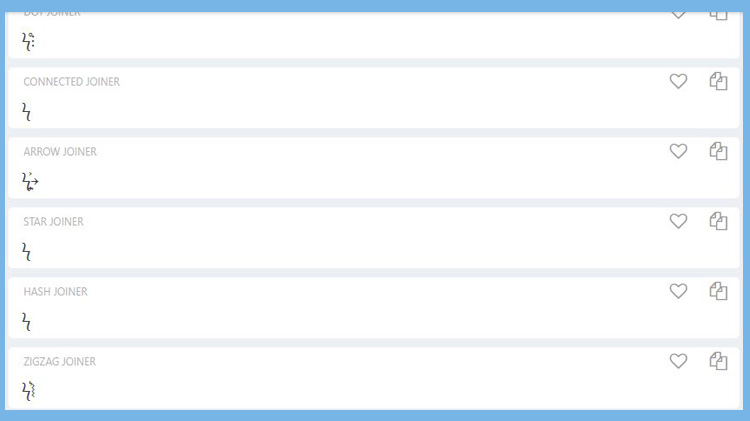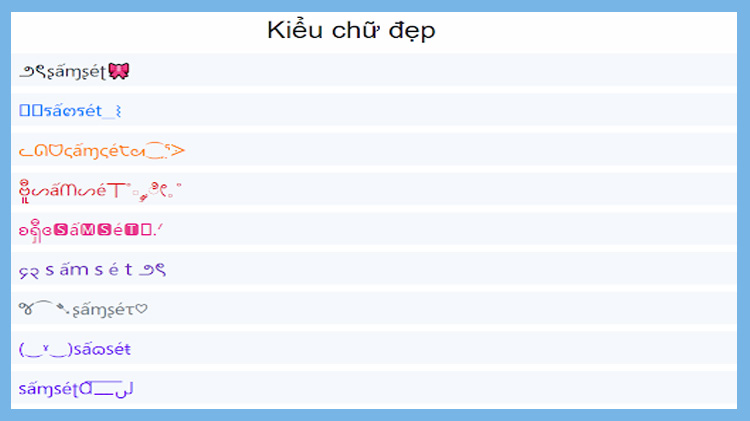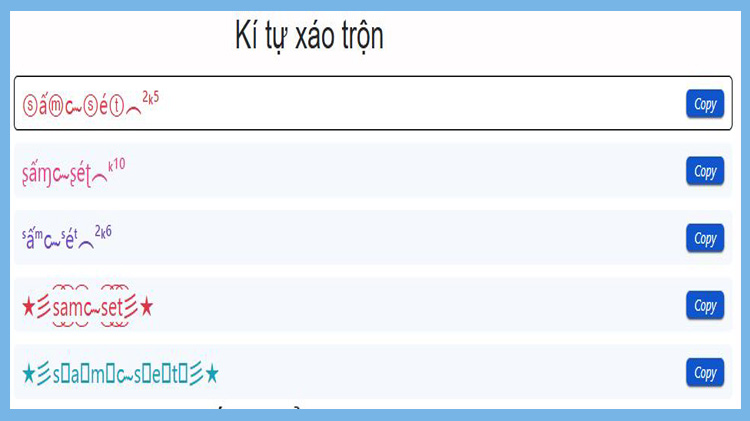
999+ Kí tự sấm sét đặc biệt, có màu sắc, đẹp và xáo trộn
Kí tự sấm sét ⚡dù chỉ là một kí hiệu nhỏ nhưng lại mang sức hút mạnh mẽ và dễ dàng thu hút sự chú ý từ người xem. Trong bài viết này, chúng tôi sẽ tổng hợp cho bạn 999+ kí tự sấm sét đặc biệt có màu sắc đa dạng và đẹp nhất hiện nay.
Những icon sấm sét đặc biệt có màu đỏ, màu xanh, màu vàng sẽ giúp bạn tạo ra dấu ấn riêng biệt khi sử dụng trên các nền tảng. Ngoài ra, Mobifonts cũng sẽ tổng hợp những chữ tia sét đẹp đến xáo trộn, đồng thời hướng cách dẫn tạo kí tự sấm sét đặc biệt theo ý muốn. Hãy cùng Mobifonts khám phá danh sách kí tự sấm sét dưới đây ngay nhé!
Những icon kí tự sấm sét đặc biệt thường được sử dụng để nhấn mạnh nội dung hoặc tạo phong cách riêng cho tên game, bài đăng hoặc bình luận. Dưới đây là bảng một số biểu tượng sấm sét phổ biến kèm tên và mã unicode mà bạn có thể sao chép và sử dụng ngay:
Bên cạnh những kí tự sấm sét thông thường, các kí hiệu sấm sét có màu đỏ ϟ, màu xanh ϟ hoặc màu vàng ϟ cũng được nhiều người ưa chuộng. Dưới đây là những kí tự sấm sét có màu sắc giúp dễ dàng thu hút sự chú ý.
Theo nghiên cứu của Smashing Magazine, màu đỏ luôn mang đến cảm giác mạnh mẽ, nổi bật và nhiệt huyết. Nếu bạn muốn thể hiện sự quyết đoán hoặc tạo ấn tượng mạnh, hãy sử dụng các kí tự sấm sét màu đỏ sau:
Màu xanh tượng trưng cho sự bình tĩnh nhưng vẫn mạnh mẽ, thể hiện sự sáng tạo và cá tính riêng biệt (Nghiên cứu của Adobe). Nếu bạn yêu thích sự mát mẻ nhưng vẫn muốn tạo dấu ấn đặc biệt, hãy thử các kí tự sấm sét màu xanh sau:
Bên cạnh 2 màu đỏ và xanh, các icon sấm sét màu vàng cũng rất được ưa chuộng vì sự lung linh và rực rỡ. Nếu bạn muốn kết hợp biểu tượng tia sét màu vàng để tạo sự nổi bật, hãy thử những kí tự sau:
Các icon chữ tia sét không chỉ đẹp mắt mà còn giúp bạn tạo dấu ấn riêng, tăng tính nhận diện và thu hút sự chú ý từ người đọc ngay từ cái nhìn đầu tiên. Dưới đây là các kiểu icon tia sét chữ đẹp mà bạn có thể sử dụng:
Ký tự sấm sét xáo trộn là sự kết hợp ngẫu nhiên giữa các biểu tượng sấm sét với các hình dạng độc đáo khác, giúp bài viết thêm phần sinh động và ấn tượng. Các mẫu kí tự sấm sét xáo trộn như sau:
Bạn muốn tạo kí tự đặc biệt sấm sét 🗲 thật ấn tượng? Chỉ cần thực hiện 3 bước đơn giản sau đây, bạn sẽ có ngay một kiểu chữ độc đáo để sử dụng trên mọi nền tảng:
Hầu hết các kí tự tia sét đều hiển thị tốt trên máy tính và điện thoại, ví dụ như ⚡ (U+26A1) hiển thị tốt trên iOS 15+ và Android 10+ nhờ được hỗ trợ trong bộ font emoji màu. Tuy nhiên một số kí tự có thể không xuất hiện trên các thiết bị đời quá cũ.
Kí tự sấm sét không chỉ mang ý nghĩa mạnh mẽ mà còn giúp nội dung của bạn trở nên nổi bật và ấn tượng hơn. Từ các icon tia sét bạn có thể thoải mái lựa chọn theo sở thích của mình. Mobifonts hy vọng rằng danh sách kí tự trên sẽ giúp bạn tìm được những kí tự đặc biệt sấm sét phù hợp nhất để sử dụng trên bất kỳ nền tảng nào!